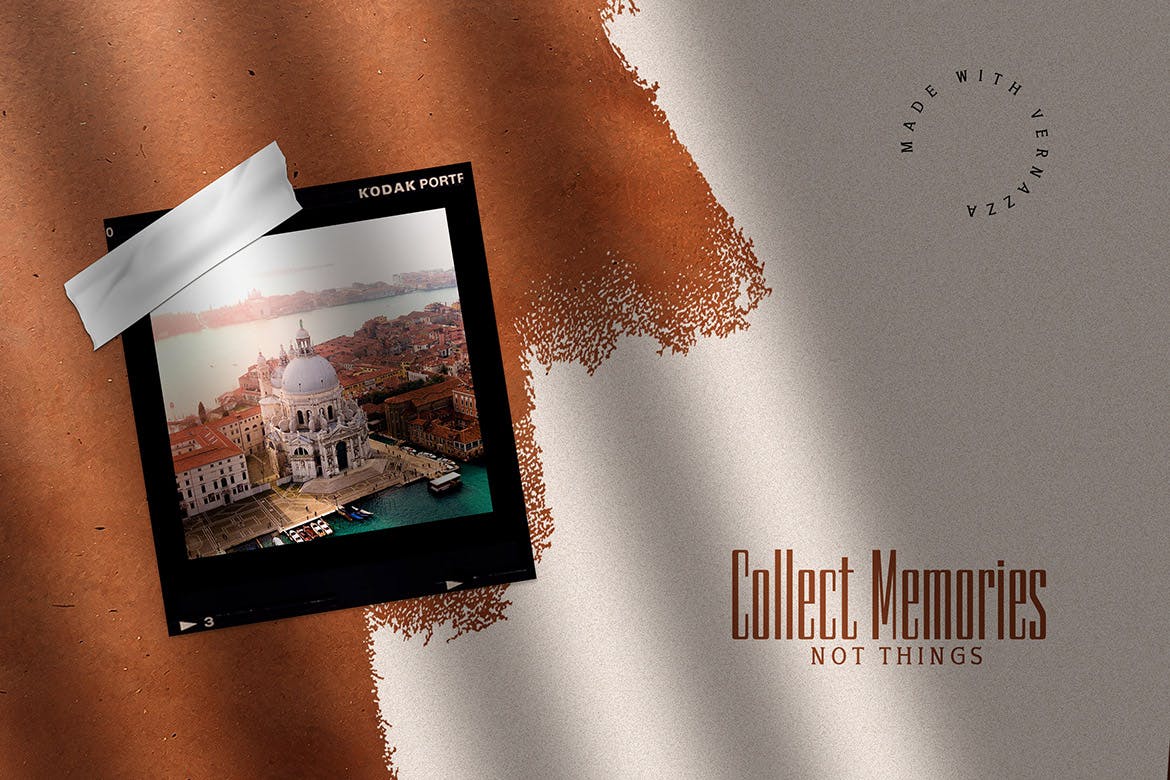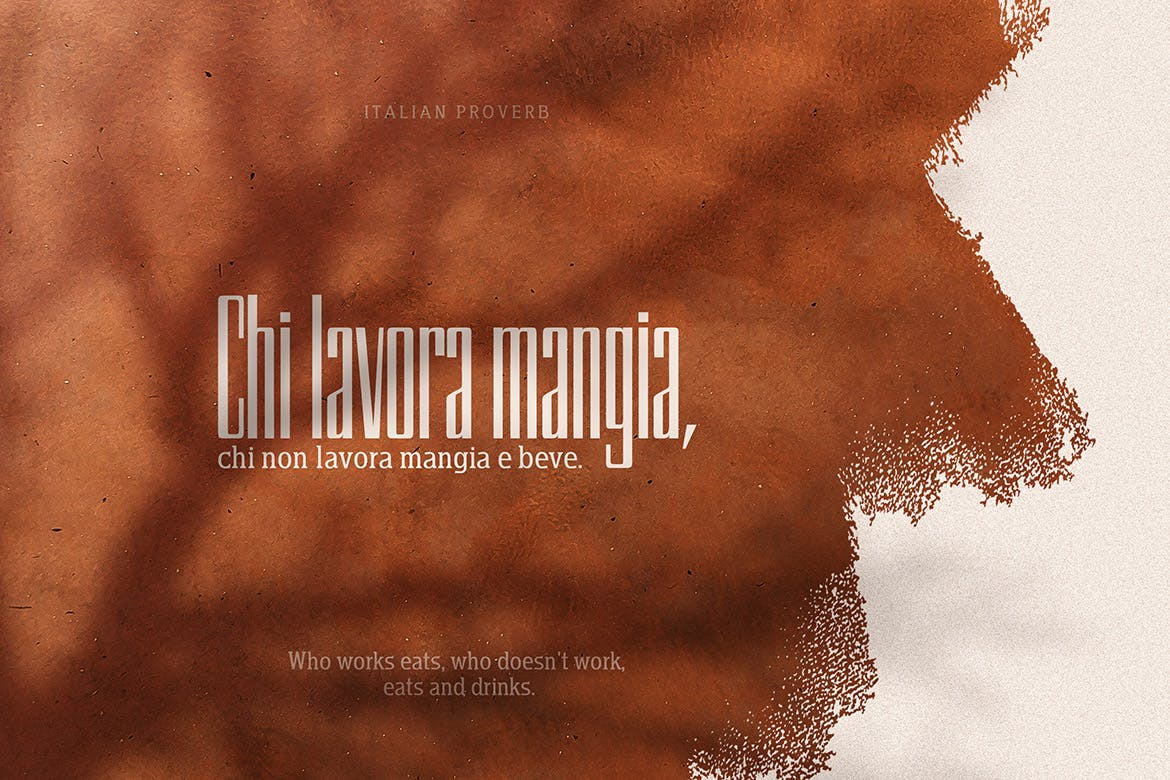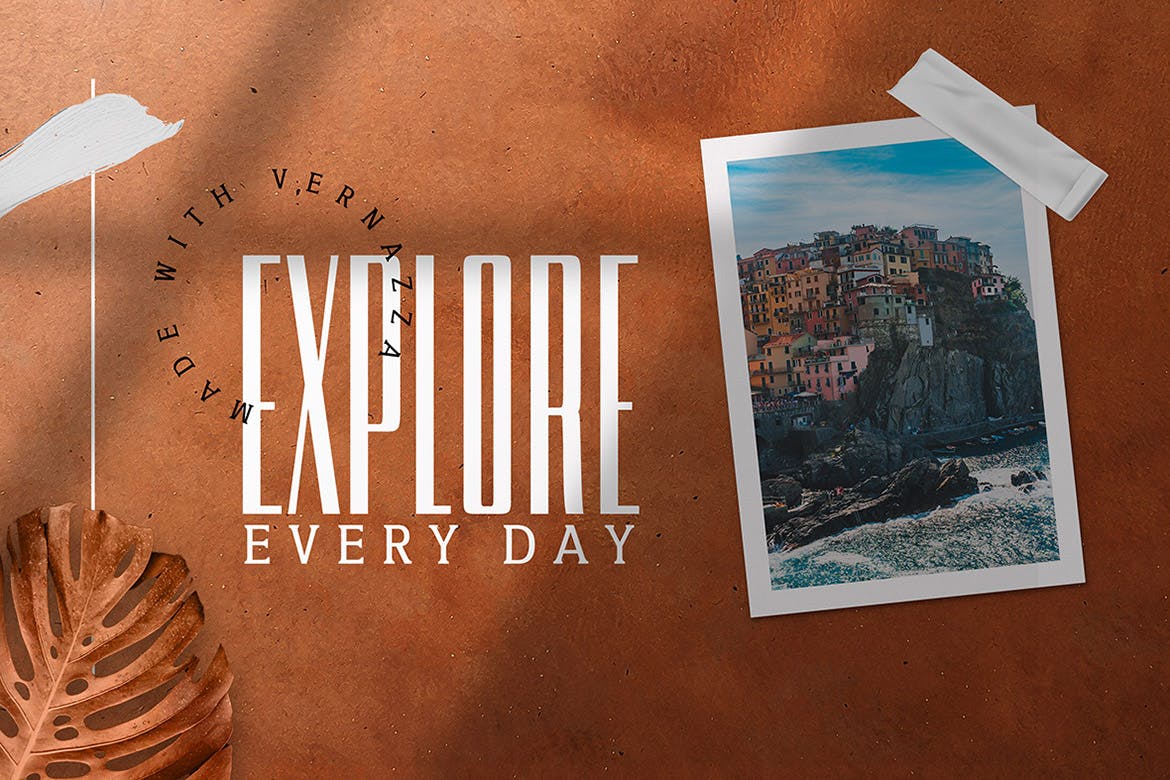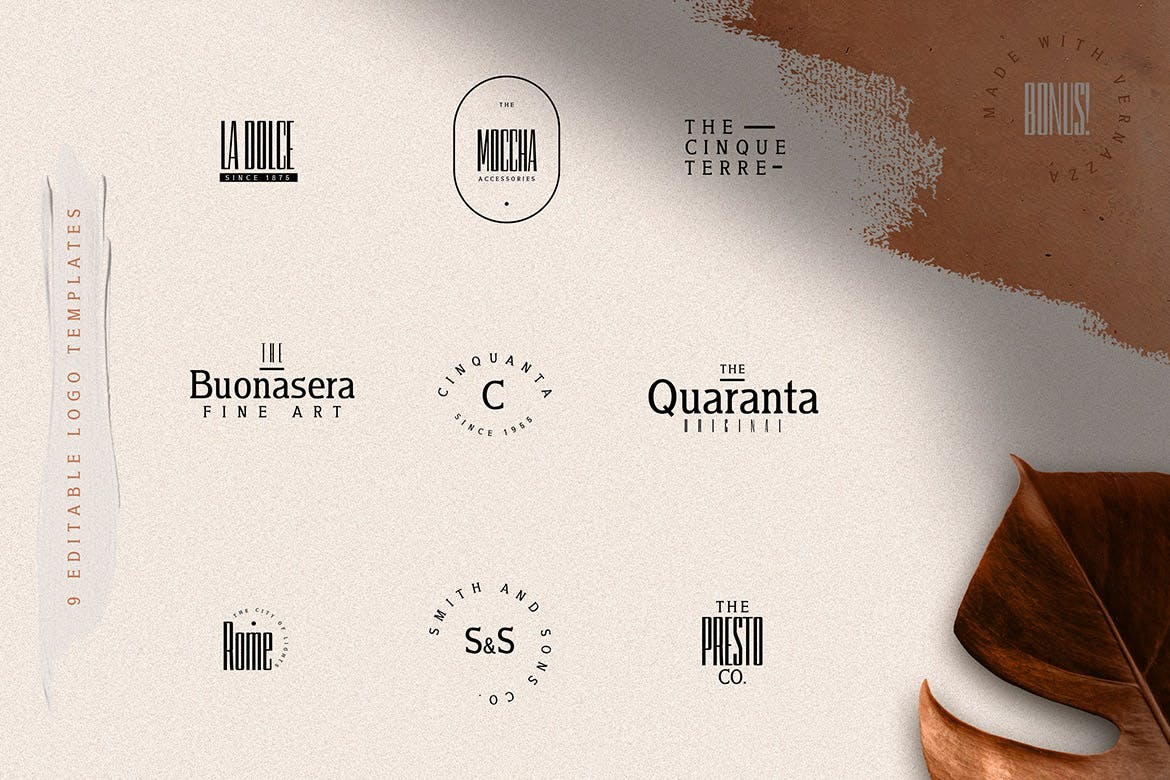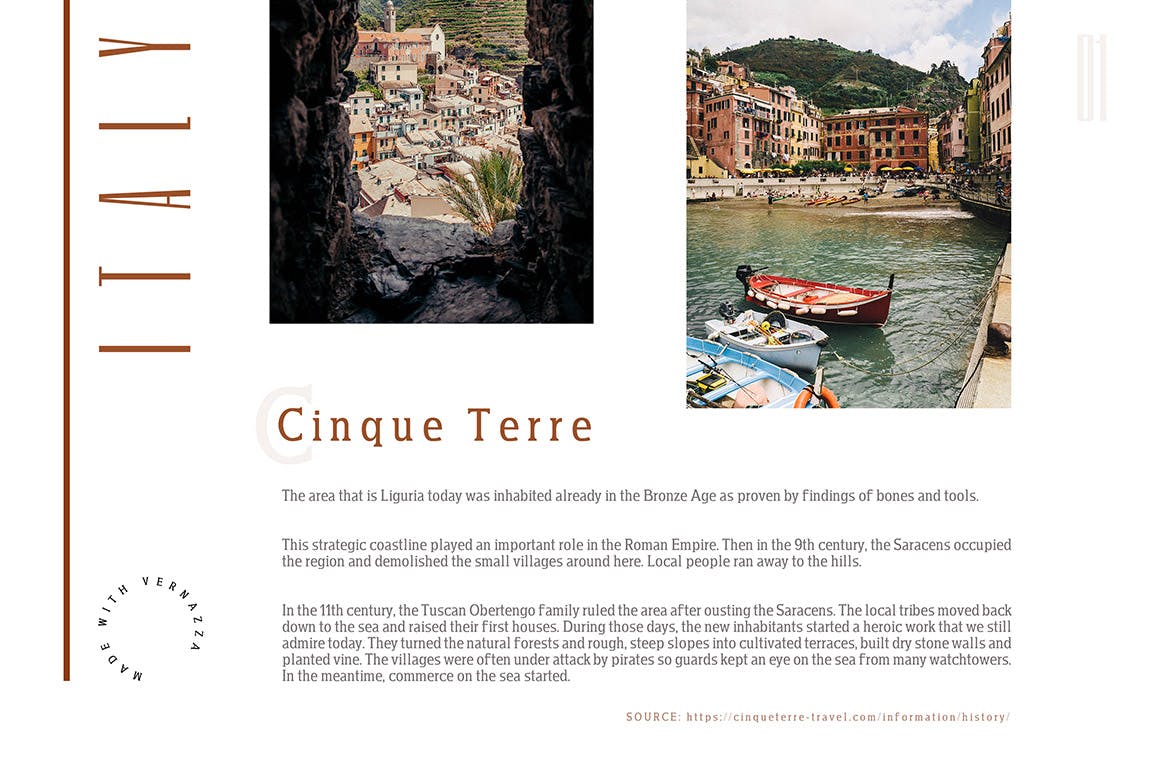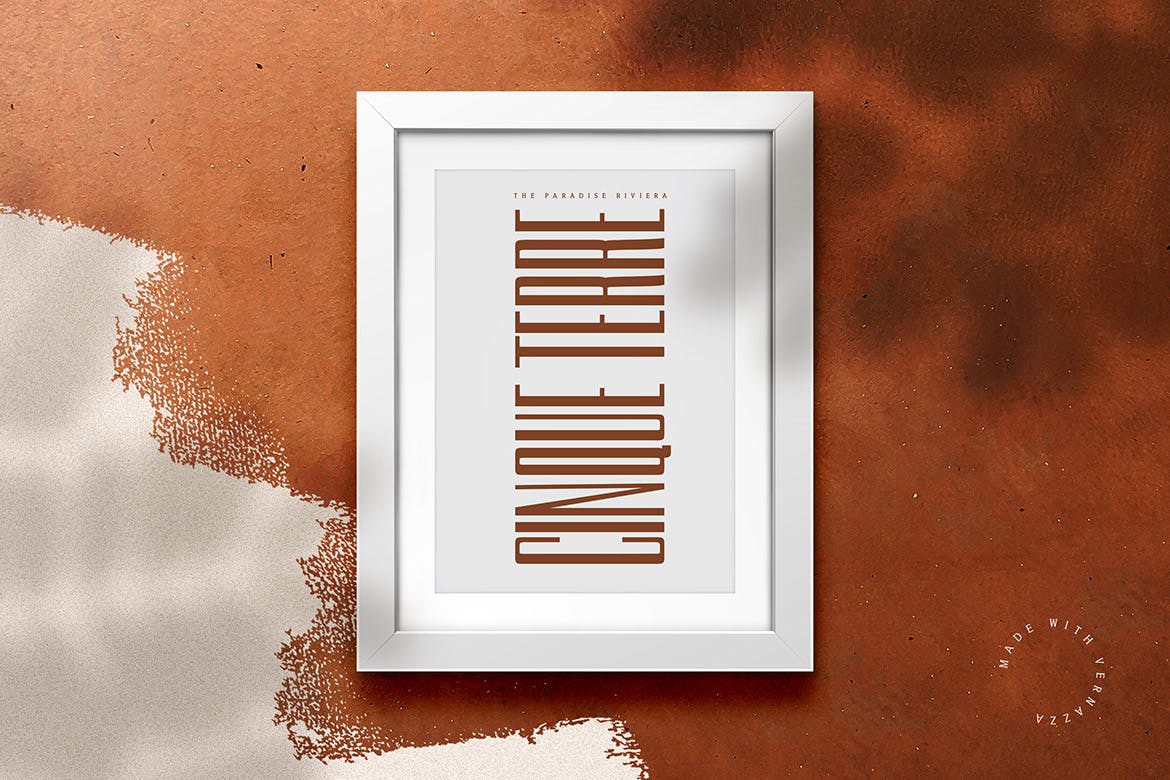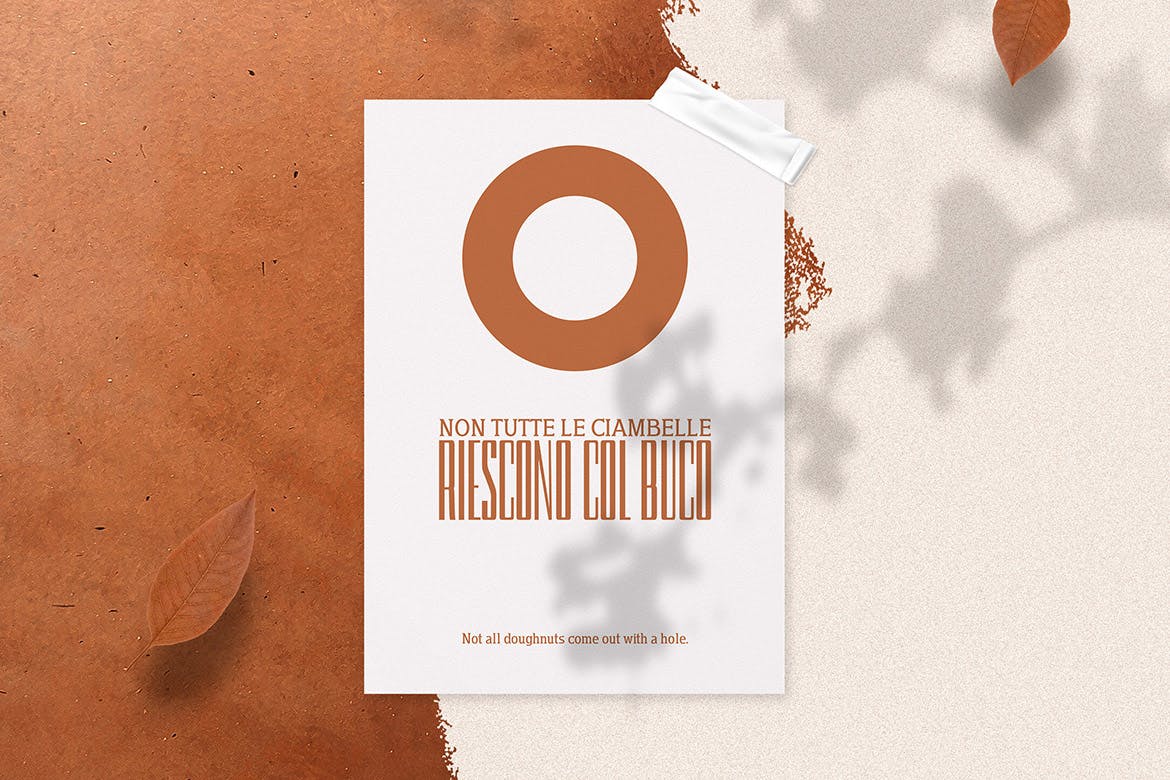
حدود ۵ سال پیش، به همراه یکی از دوستان خوبم تصمیم گرفتیم که سفری را آغاز کنیم و از طریق اروپا به ایتالیا، به منطقهای به نام چنکوه تِره برویم. این منطقهای کوچک در سواحل دریای لیگوری است که دارای روستاهای دیدنی، سواحل زیبا و چشماندازهای شگفتانگیز میباشد. چنکوه تِره و ورنازا، که شهری کوچک در این منطقه است، تأثیری ماندگار بر روی من گذاشت و این فونت نتیجهی آن سفر است.
فونت ورنازا ترکیبی از دو فونت است - یک فونت سریف شیک و یک فونت سانس سریف بلند. این فونت به شما کمک میکند تا در طراحیهای خود حس لوکس و در عین حال کمی روستایی را ایجاد کنید و در عناوین بزرگ، لوگوها و پاراگرافهای کوچک به خوبی کار میکند. شما میتوانید این دو فونت را به شیوههای نامحدودی ترکیب کرده و لوگوهای منحصر به فردی بسازید. علاوه بر این، شما ۹ ماکاپ لوگو رایگان که با فونت ورنازا طراحی شدهاند را دریافت خواهید کرد که میتوانید آنها را به دلخواه خود در Adobe Illustrator ویرایش کنید.